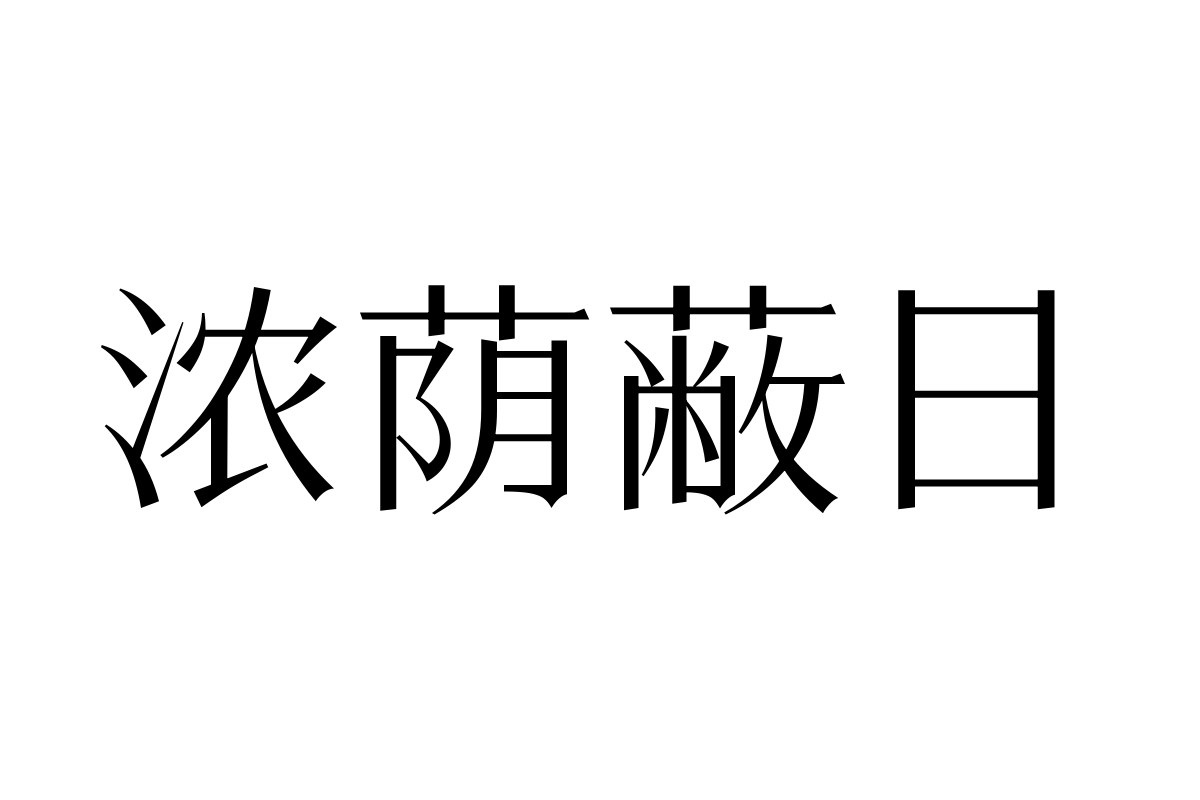
三极黑宋体是一种具有纤细风格的中文字体,它由三个不同的字形构成,分别是粗体、中体和细体。这种字体的特点是笔画细腻、线条流畅,给人一种优雅而精致的感觉。
三极黑宋体适用于需要强调文字细节和美感的场合,如设计海报、杂志、广告等。它的笔画粗细变化丰富,能够很好地展现文字的层次感和空间感,使整体设计更加和谐美观。
此外,三极黑宋体的纤细风格也使其在排版时具有较高的可读性,能够更好地传达文字内容。同时,该字体还具有一定的装饰效果,可以在需要强调重点或增加艺术感的场合使用。
总之,三极黑宋体是一种非常优秀的中文字体,适合用于各种需要强调文字细节和美感的设计项目。